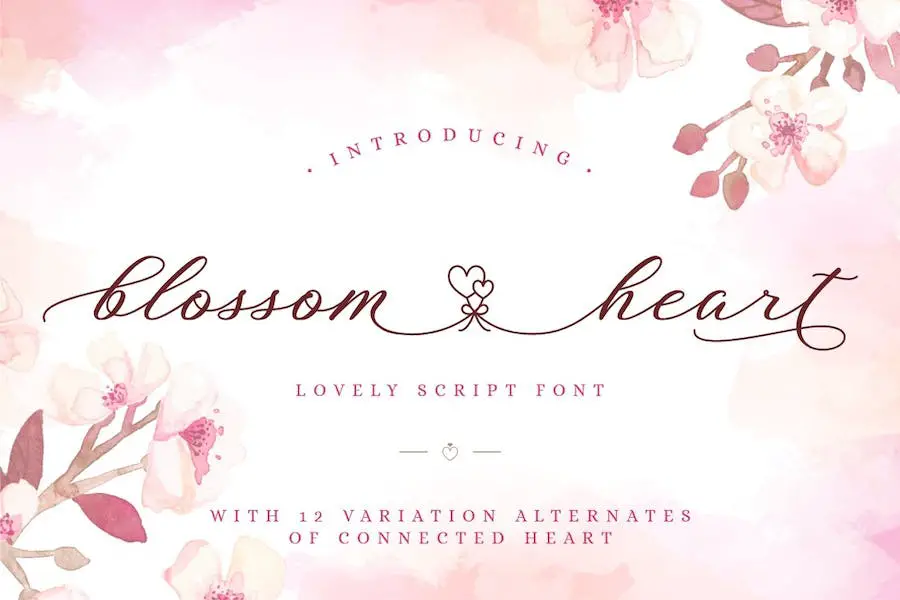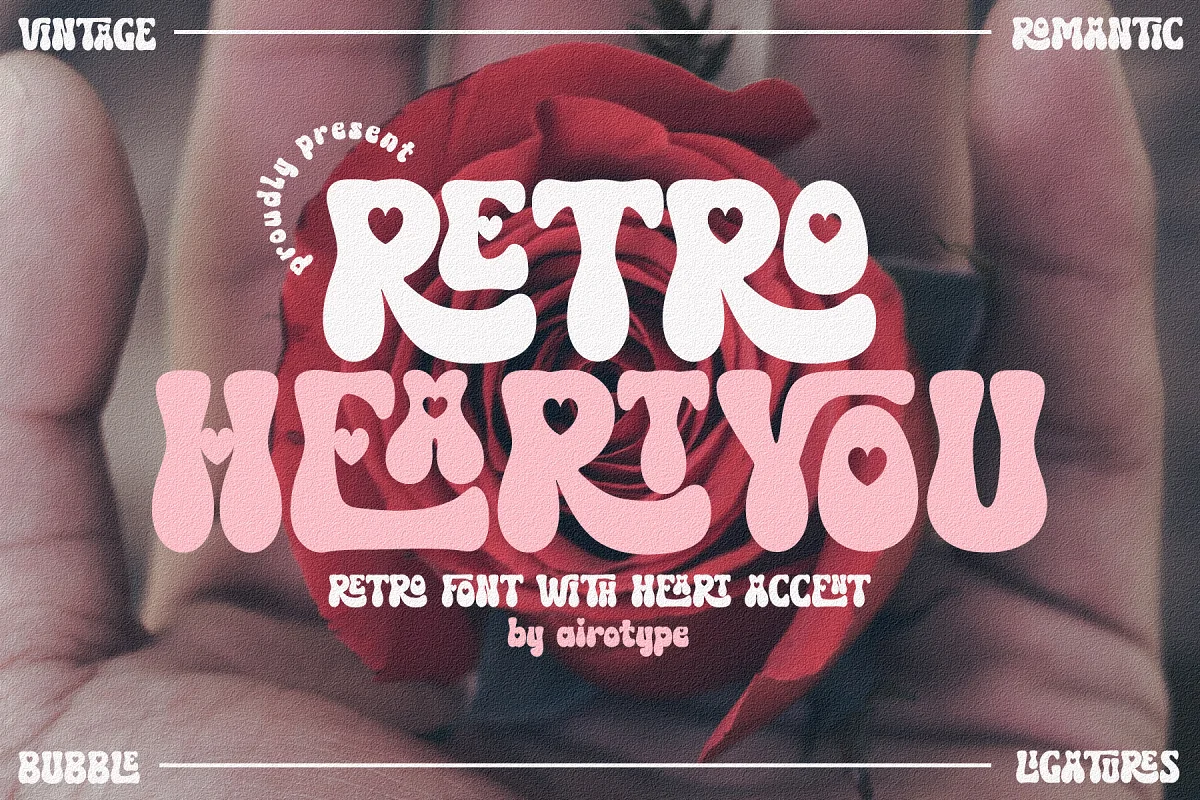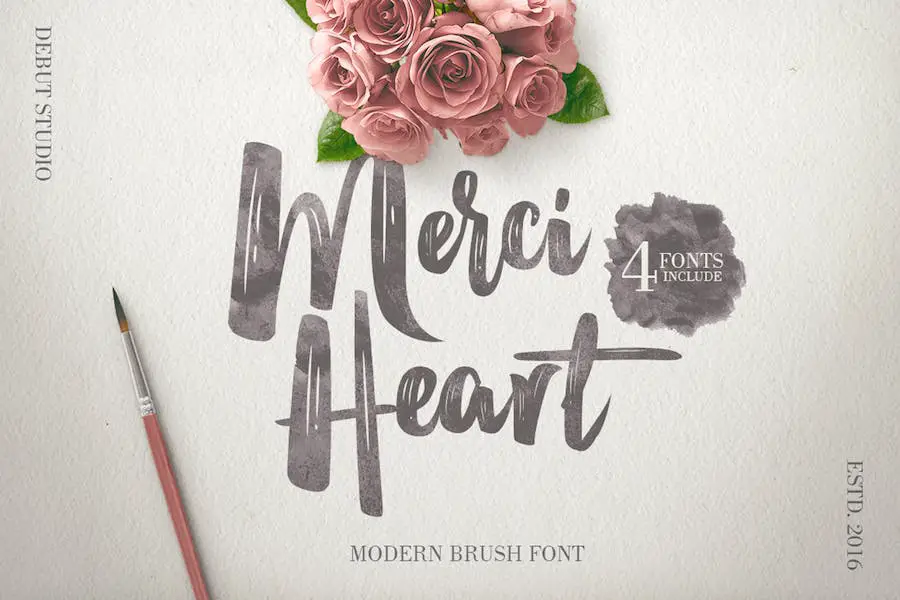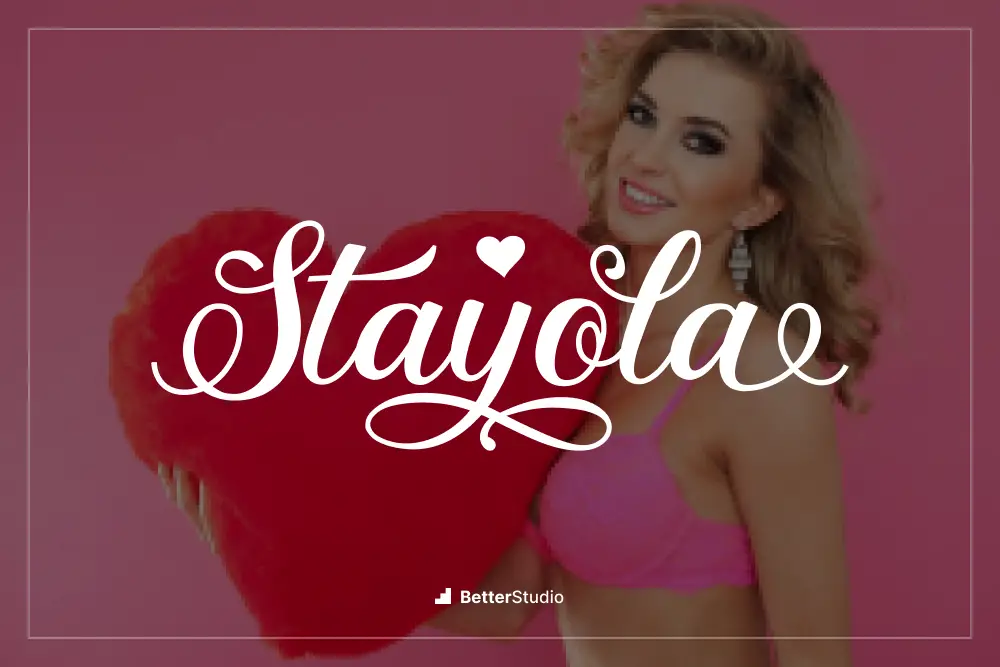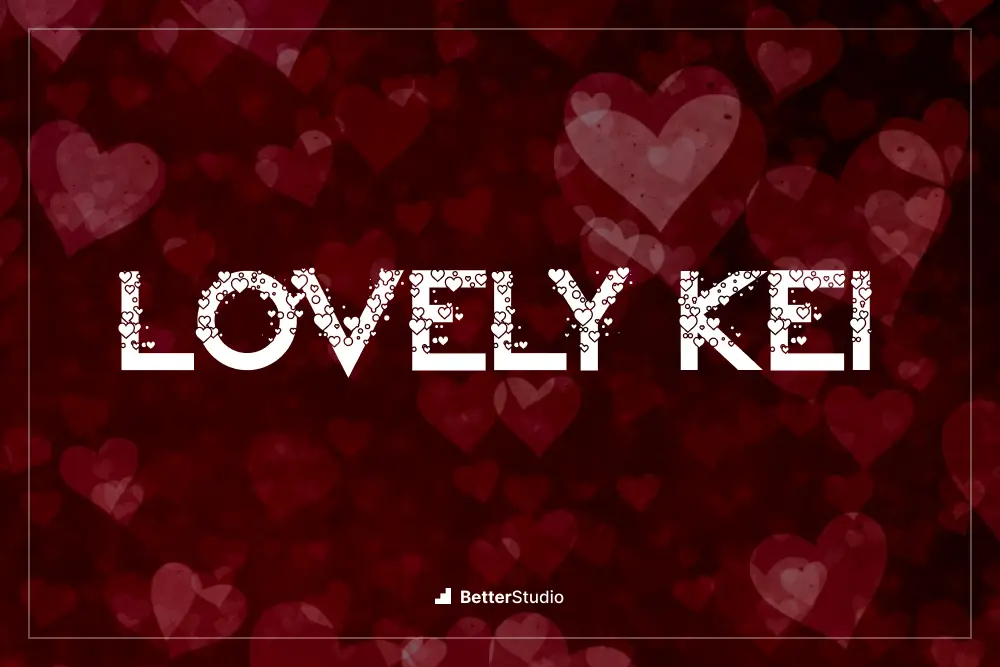
أفضل 15 خطًا على شكل قلب ️ 2023 (مجاني ومميز)
نشرت: 2023-05-20هل شعرت يومًا أن شيئًا ما كان مفقودًا في مشاريع التصميم الخاصة بك؟ ربما حان الوقت لإضافة القليل من الحب مع بعض خطوط القلب. ولكن مع وجود العديد من الخيارات ، كيف تعرف أيها تختار؟
في هذه المقالة ، قمنا بتجميع قائمة بأفضل 15 خطًا للقلب ستساعد في نقل تصميماتك إلى المستوى التالي. لن تضيف هذه الخطوط اهتمامًا مرئيًا فحسب ، بل ستثير أيضًا المشاعر وتخلق تجارب لا تُنسى لجمهورك.
هل تعلم أن دمج العناصر الانفعالية في تصميماتك يمكن أن يزيد المشاركة بنسبة تصل إلى 80٪؟ تعد إضافة خطوط القلب طريقة دقيقة لكنها قوية لتحقيق ذلك. لذا ، سواء كنت تصمم دعوات زفاف أو بطاقات عيد الحب ، فمن المؤكد أن هذه الخطوط ستثير إعجابك.
في الفقرات التالية ، سنتعمق في كل خط ، مع إبراز ميزاته الفريدة وتطبيقاته المحتملة. هيا بنا نبدأ!
أفضل الخطوط قسط القلب
إذا كنت مصمم رسومات تتطلع إلى نقل مشاريع التصميم الخاصة بك إلى المستوى التالي ، فتأكد من مراجعة أفضل خطوط القلب المتميزة هذه. لن ترغب في تفويت الخيارات الفريدة والأنيقة التي ستجعل تصميماتك مميزة!
أعراض العشق
Love Struck هو خط رائع لعيد الحب يتضمن رموزًا مرحة! يأتي هذا الخط الرائع والممتع مع دعم متعدد اللغات ويتضمن 26 حرفًا كبيرًا و 26 رسمًا مبتكرًا في أماكن صغيرة وأرقام ورموز.
خطوط قلب Google هي كل الغضب هذه الأيام ، و Love Struck هو إضافة ممتازة لمجموعة أي مصمم. مع رموزه الساحرة وواجهة سهلة الاستخدام ، يعد هذا الخط مثاليًا لإنشاء تصميمات رائعة لعيد الحب أو أي مشروع آخر يتطلب لمسة مرحة.
سرقة القلوب
Stealing Hearts هو خط ساحر سيسرق العرض في أي مشروع تصميم. يعد محرف النص المكتوب بخط اليد هذا مثاليًا للمبدعين الذين يرغبون في جذب انتباه جمهورهم بأسلوب أنيق وفريد من نوعه.
سواء كنت تصمم دعوات أو تنشئ رسومات وسائط اجتماعية ، فإن Stealing Hearts ستجعل مشروعك مميزًا.
واحدة من أبرز ميزات Stealing Hearts هي الأحرف المزدوجة الجميلة ، والتي تضيف لمسة إضافية من الأناقة إلى النص الخاص بك. بالإضافة إلى ذلك ، يتضمن الخط مجموعات أسلوبية تسمح لك بتخصيص رسائلك بشكل أكبر.
يضمن تشفير PUA أن الخط متوافق مع برنامج Adobe ، مما يسهل دمجه في تصميماتك الحالية. أخيرًا ، تسمح الأرقام وعلامات الترقيم المضمنة في الخط بالتكامل السلس في أي مشروع.
صورة ظلية القلوب
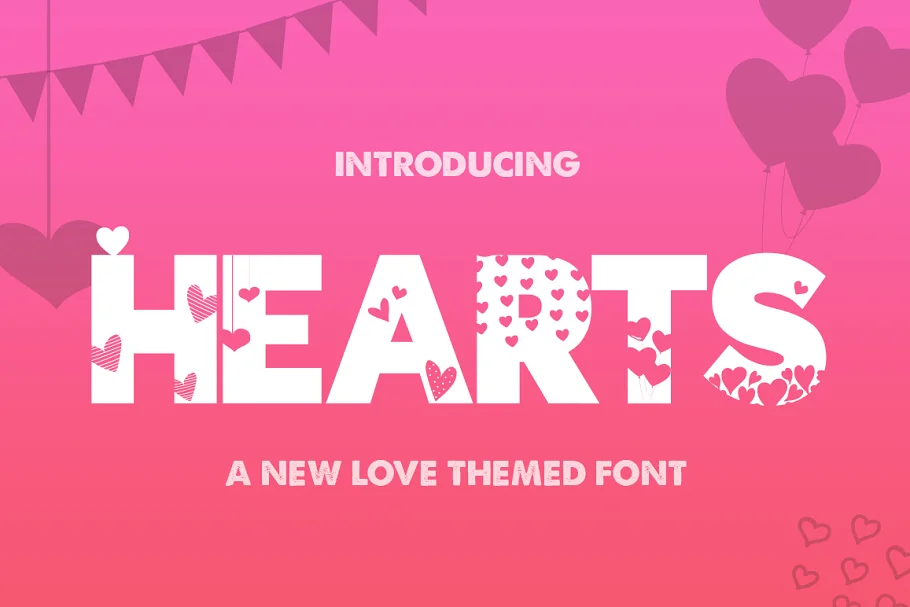
Hearts Silhouette هو خط يمكن لمصممي الجرافيك استخدامه لإضافة لمسة حب إضافية لمشاريعهم.
يضيف The Hearts Silhouette Script لمسة أنيقة لأي مشروع تصميم مع تصميماته الفريدة على شكل قلب مدمجة في كل حرف.
سيكون هذا الخط مثاليًا للدعوات أو بطاقات المعايدة أو حتى الملاحظات الشخصية للأحباء. من المؤكد أن أسلوبه المرح والمتطور سيثير الإعجاب ويضيف لمسة شخصية إلى أي مشروع.
قلب الشوكولاتة
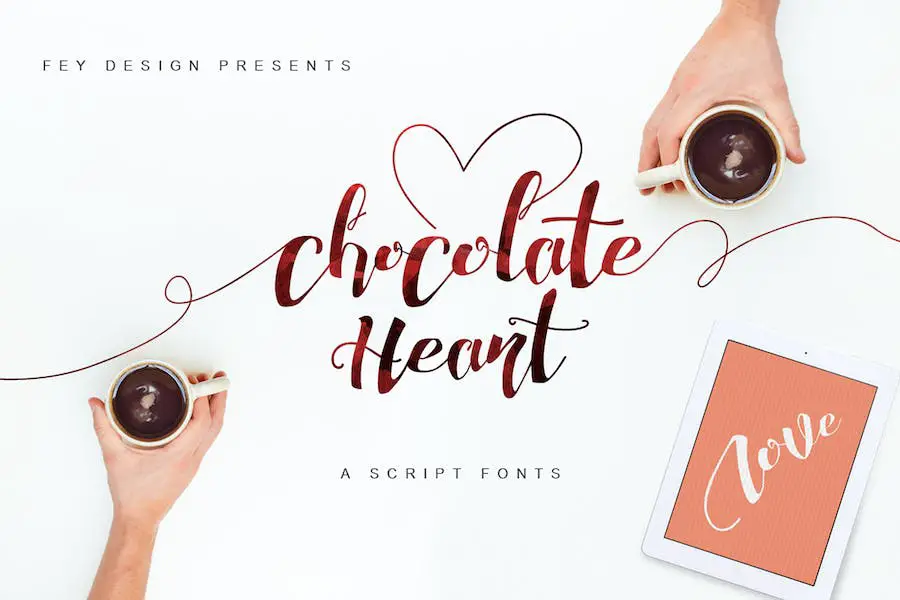
قلب الشوكولاتة هو محرف خط حديث سيضيف لمسة فريدة لمشاريع التصميم الخاصة بك. يعتبر خط النص هذا مثاليًا لإضافة الأناقة والتطور إلى دعوات الزفاف والشعارات والشارات والملصقات والقمصان وأي تصميمات أخرى للعناصر.
يأتي هذا الخط مزودًا بميزات OpenType ، بما في ذلك الحروف المركبة القياسية والمجموعات النمطية والأحرف متعددة اللغات ، مما يمنحك الكثير من الخيارات لتخصيص تصميماتك.
بالإضافة إلى ذلك ، يتيح لك الجمع بين خطوط الربط البديلة إنشاء المزيد من التصميمات الفريدة والجميلة.
يا حب
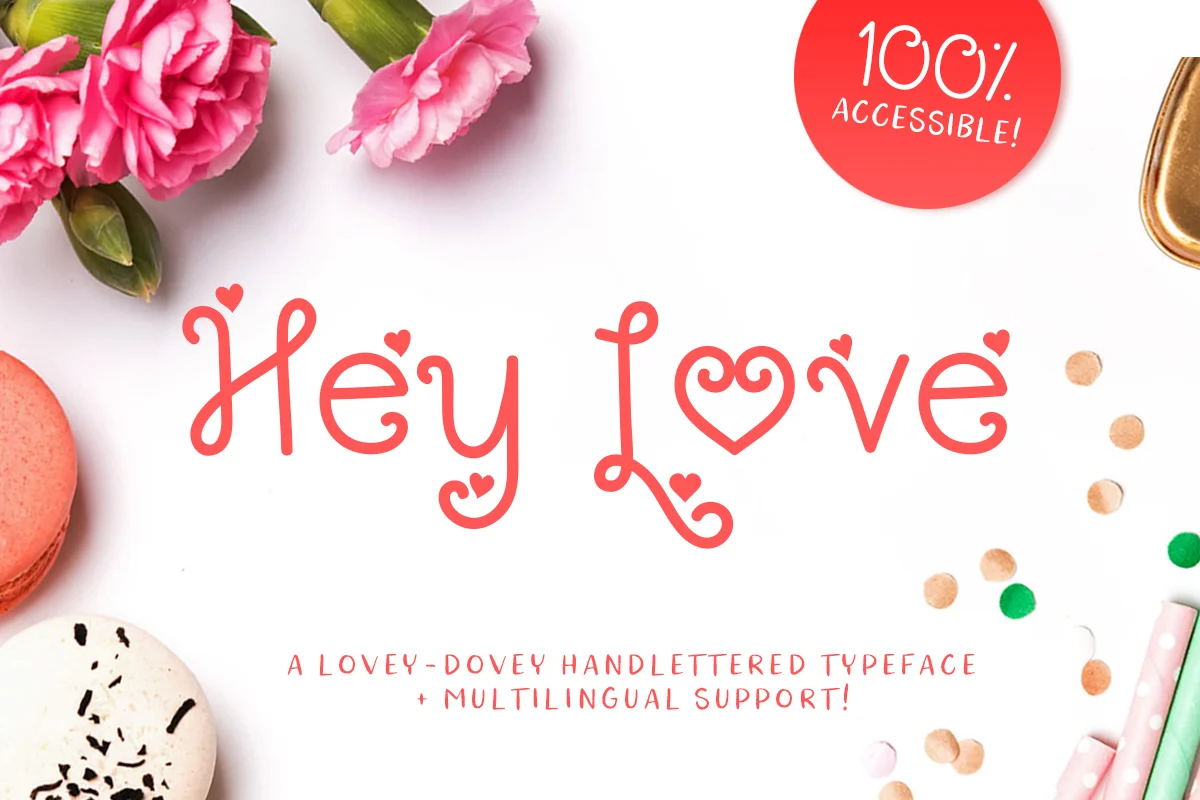
Hey Love عبارة عن محرف نصي مكتوب بخط اليد ينضح بالحب والرومانسية بأسلوبه الأحادي. إنه الخط المثالي لتصميمات عيد الحب ، والحرف اليدوية ، والمشاريع الأخرى التي تتطلب لمسة من الحب.
تعدد استخداماته يجعلها مثالية للشعارات والاقتباسات ورؤوس المدونات والدعوات والعلامات التجارية والقمصان والملصقات والمزيد.
ما يميز Hey Love عن الخطوط الأخرى هو العديد من الأحرف البديلة ، والتي تأتي مع دعم متعدد اللغات.
هذا يعني أنه يمكنك الوصول إلى جميع الأحرف الإضافية دون الحاجة إلى أي برنامج تصميم خاص. بالإضافة إلى ذلك ، يمكن للجميع الوصول إلى هذا الخط بنسبة 100٪ نظرًا لأنه مشفر بواسطة PUA.
قلب جميل
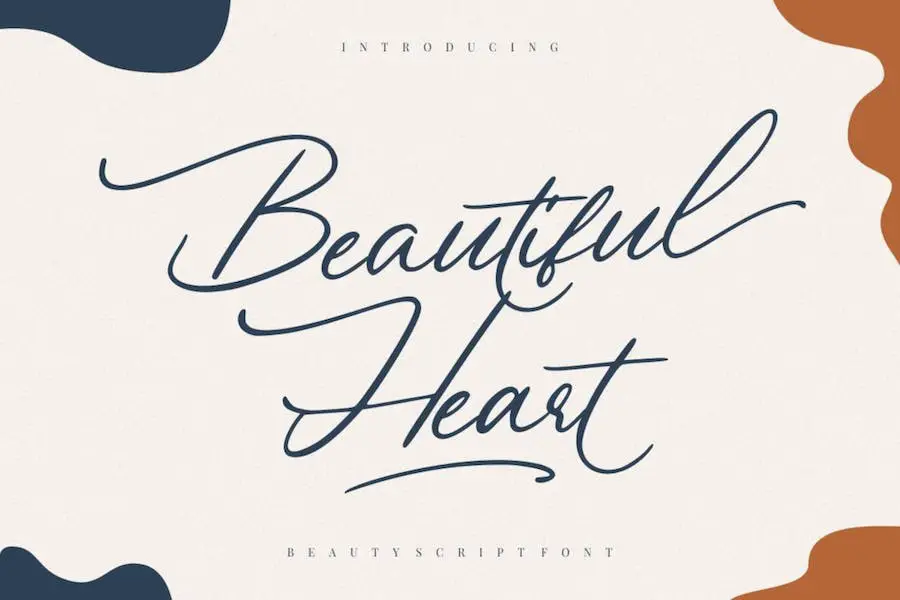
Beautiful Heart هو خط نصي للخط يمكنه رفع أي مشروع بلمسة الفرشاة الطبيعية. إنه مثالي للتصاميم مثل الشعارات والدعوات وتصميمات الزفاف والقرطاسية.
يعمل هذا الخط أيضًا بشكل جيد مع منشورات الوسائط الاجتماعية والإعلانات وتغليف المنتجات والملصقات والتصوير الفوتوغرافي والعلامات المائية والمناسبات الخاصة.
إحدى الميزات البارزة لـ Beautiful Heart هي المجموعة الكاملة من الأحرف الكبيرة والصغيرة ، والتي تتضمن رموزًا وأرقامًا وعلامات ترقيم متعددة اللغات.
بالإضافة إلى ذلك ، يتضمن هذا الخط وصلات ربط وبدائل أسلوبية ومجموعات أسلوبية وحروف مائلة ، وكلها تضيف عمقًا وشخصية لمشاريعك.
ملاحظات بيلا
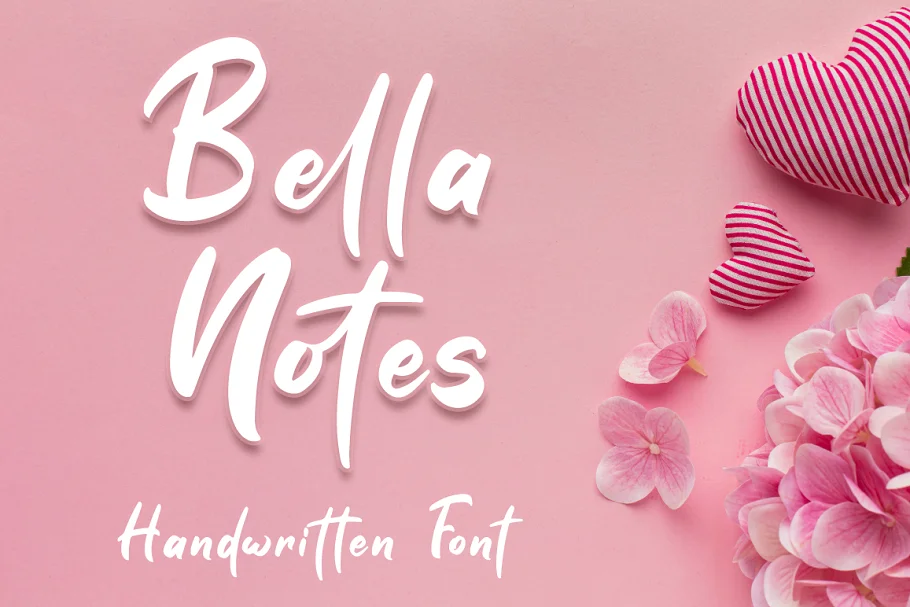
Bella Notes عبارة عن خط جميل مكتوب بخط اليد يجذب انتباهك بالتأكيد. يأتي هذا الخط بأحرف ربط تجعله مثاليًا لمجموعات تصميم مختلفة.
يعد Bella Notes اختيارًا ممتازًا إذا كنت تبحث عن خط يتوافق مع سمة عيد الحب ، أو أي منتج مثل أغلفة الكتب والقمصان والعلامات التجارية والترويج ومنشورات الوسائط الاجتماعية والاقتباسات وحفلات الزفاف والتصوير الفوتوغرافي وغير ذلك.